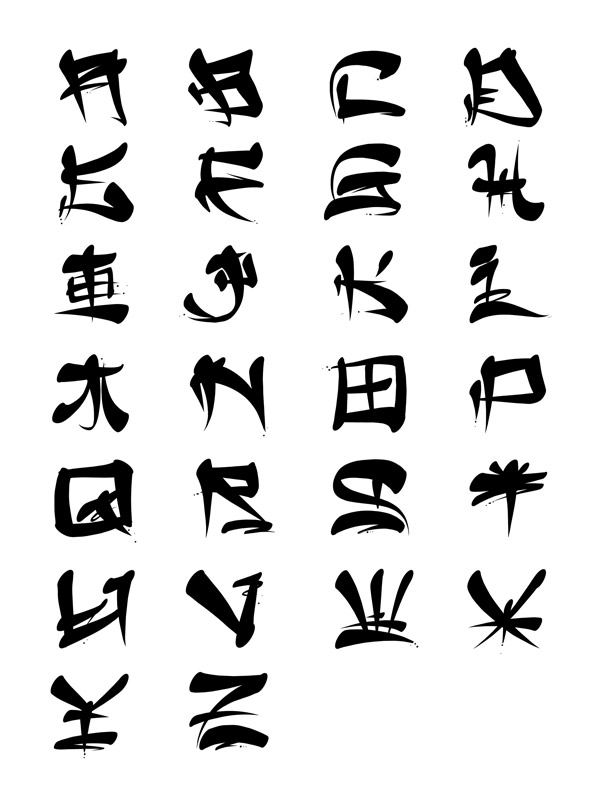
50+ шрифтов в японском и китайском стиле (английские и кириллица)
Что-то давно у нас не было оригинальных шрифтов в блоге. Последний пост и этой рубрики посвящался страшным хоррор шрифтам, которые легко можно использовать для открыток/иллюстраций на хеллоуин. Если же вам надо создать графику в азиатском стиле, то сегодняшняя подборка как раз для вас. Сначала будут материалы с англоязычным алфавитом, а после них — с поддержкой кириллицы.
По аналогии со статьей про японские и китайские логотипы мы решили совместить оба направления в одной заметке. Вряд ли, большинство пользователей сможет отличить шрифты в китайском стиле от японских иероглифов. Не удивительно, что даже крупные каталоги шрифтов группируют эти направления в одну категорию. Поэтому просто выбирайте один из вариантов ниже, который больше всего соответствует вашей задаче и стилистике.
Shanghai
Shojumaru
Bonzai
Kato
Electroharmonix
Karate
Hong Kong Hustle
Hirosh
Chinese Takeaway
Gang of Three
Yama Moto
Japanese 3017
Yonezawa
Japanese Style Font
Asian Guy
Korean Calligraphy
В принципе, в данной подборке можно заменить не только японские иероглифы и шрифты в китайском стиле, но также встречаются корейские, тайские и некоторые другие азиатские направления.
DomoAregato
Pauls Kanji
Chow Fun
Seven Monkey Fury BB
Kashima Brush
Просматривая иллюстрации к посту, мы видим, что шрифты в японском стиле (и не только) лучше воспринимаются с определенным сопутствующим оформлением будь то тематический фон, соответствующая палитра цветов или дополнительные объекты на картинке.
Samurai
Manglo
Chinese Dragon
Konfuciuz
Kingthings Conundrum
Far East
Hirakatana
Chinese Asian Style Font
Yozakura
Kaneiwa Alp
Made in China
Pho Tai
Music Warrior
Odishi
Osaka-Sans Serif
Real Chinese
Manga
JSA Lovechinese
Sudoku
Night in Tokyo
All Yoko
Not the far east
Шрифты в китайском и японском стиле кириллица
NipponCyr
PresentScript Cyrillic
ChinaCyr Regular
Tokio
DSJapanCyr Normal
MandarinC
Keetano Gaijin
RUSMadeinChinav2
Chinyen
Shanghai_RUS
Итого в заметке получилось чуть более 50-ти классных и оригинальных шрифтов в японском и китайском стилях для создания тематических картинок/иллюстраций в Фотошопе. Они могут использоваться для открыток, приглашений, документов, в графическом оформлении сайтов, для соцсетей и т.п.
30 шрифтов в китайском стиле
Шрифты являются полезным ресурсом для любого дизайнера. С их помощью вы сможете придать определенный стиль и выразить смысл своей работы. В шрифтах, также как и в дизайне, есть множество направлений. Они могут быть простыми и чистыми, с потеками краски в стиле гранж, урбанистическими, восточными, фигурными и так далее.
В сети таких ресурсов великое множество, но на их поиски приходится тратить немало времени. В этой подборке, вам предоставлена возможность загрузить 30 шрифтов, выполненных в китайском стиле. Все они абсолютно бесплатны. С их помощью вы сможете преобразить любую работу, создание которой навеяно “Китайским Новым Годом”!
Шрифт Chow Fun
Shanghai шрифт
Шрифт под названием Karate
Техничный шрифт Technojap
Милый шрифт Cute Line
Шрифт в китайском стиле Hirosh
Аккуратный шрифт в китайском стиле Gang of Three
Шрифт в стиле набросков Takeout
Чистый каллиграфический шрифт Wonton
Шрифт в каллиграфическом стиле Yorstat
Креативный угловатый шрифт Sheru Pro
Необычный шрифт Manglo
Шрифт Electro в виде иероглифов
Шрифт Osaka Sans
Manga шрифт
Шрифт Made in China
Узорный шрифт Love Chinese
Креативный шрифт Yama Moto
Крупный жирный шрифт Nuku Nuku
Крупный китайский шрифт Chinyen
Тонкий шрифт Shai
Шрифт Chang Chang
Заглавный шрифт в китайском стиле Tsa
Четкий равномерный шрифт Light Morning
Контурный шрифт Ninja Line
Крупный жирный шрифт Ginko
Китайский изогнутый шрифт Deng Thick
Жирный угловатый шрифт Rufcut
Жирный шрифт Seven Monkey
Шрифт в стиле дальнего востока Far East